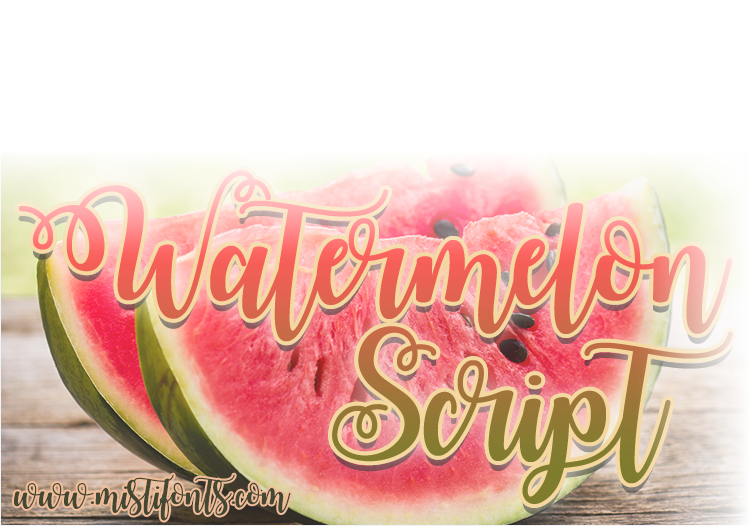
A Watermelon Script Font oferece uma experiência de escrita que transmite calor, frescor e diversão com um toque suave. Perfeita para quem busca uma fonte elegante para trabalhos de arte gráfica, marketing ou design editorial, esta fonte adocicada é a escolha perfeita. Com traços finos e formas fluidas, você pode criar mensagens frescas e memoráveis, ideal para aplicativos como cartões de aniversário, logotipos de lojas de gelatina ou qualquer projeto que valorize um toque leve, cheio de vida e alegria. A designer Misti’s Fonts trouxe à tona uma fonte escrita a mão com um touch suave de água de limão, criando o ambiente ideal para criar arte gráfica divertida e sofisticada no Brasil.